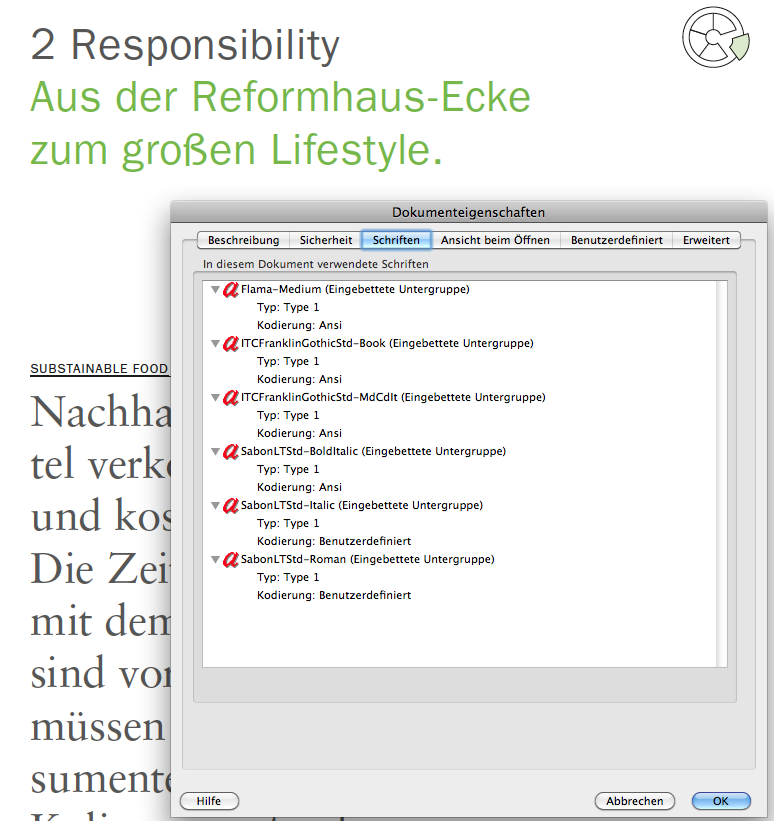
Erkennt jemand diese Schrift?
kann mir jemand helfen und mir sagen was das für ein Schrift ist? Ich konnte es bis jetzt leider noch nicht herausfinden :(
Jene werden in dem pdf verwendet:
Vielen vielen Dank euch Beiden für die schnelle Antwort!
Hab mir schon fast gedacht dass es ein Gothic-Verschnitt ist...
Aber Bertel, wie konntest du das pdf in voller Ansicht sehen und dazu auch noch die Dokumenteigenschaften öffnen?! Ich steh auf dem Schlauch :)
Ich hab
- google angeschmissen
- nach "2 Responsibility Aus der Reformhaus-Ecke zum großen Lifestle" gesucht.
Das führte zu einem pdf von GREY Foodtrends, das hab ich
- runtergeladen
- geöffnet,
- mit ?D hineingeschaut,
- einen Screenshot gemacht und
- geposted.
(Sag bloß, du hast das pdf schon gehabt und hättest selbst nachschauen können? Das wär ja ’n Ding … :lol: )
Ja hab ich... daher hab ich ja den Screenshot. Schande über mein Haupt! :P
Aber ich muss gestehen dass ich den Kniff nich kannte... und das soll mit nem Standard Asobe Reader funktionieren?! mmh
Ja, das geht mit dem Reader genau so mit ?D, ich hab’s grad ausprobiert (Reader 9.4.0) :D
Wäre das nicht mal einen Wiki-Eintrag wert? Es kommt doch häufiger vor, dass die Funktion, eine Schrift in einer pdf-Datei auszulesen, nicht bekannt ist.
… Aber wollen wir das wirklich?
Nö! So ein paar kleine Erfolgserlebnisse möchte ich einfach haben. :lol:
Man kann ja im Schrift-gesucht-Forum eine Meldung anpinnen, die erklärt, wie man Schriften aus PDFs ausliest, wie man WhatTheFont benutzt und dass man erstmal schauen soll, ob es nicht doch wieder die Rotis ist.
Aber wollen wir das wirklich?
lösung verraten ist eh okay. ich glaub das machen wir alle am liebsten. aber so ein kleiner link zu einer anleitung würde uns ersparen, den ?-D-schmäh jedesmal hinschreiben zu müssen.